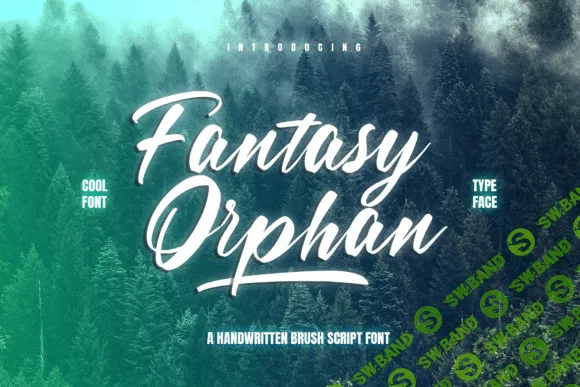
Название: Fantasy Orphan Font
Fantasy Orphan - милый и дружелюбный рукописный шрифт.
Его естественный и неповторимый стиль делает его невероятно подходящим для большого бассейна дизайна.
Единственный предел - ваше воображение!